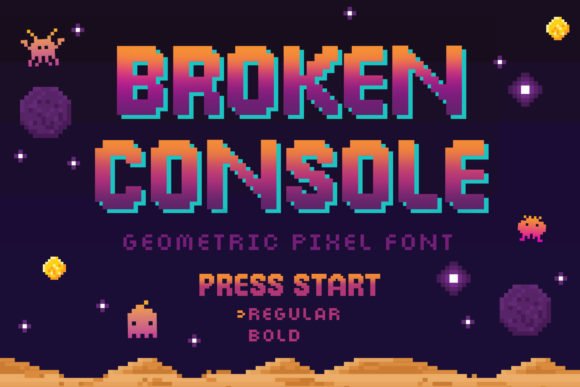
[Creativefabrica] Broken Console Font (2021)
Broken Console - это современный и футуристический шрифт.
Этот шрифт идеально подходит для написания веб-дизайнов, визитных карточек и практически всего, что требует холодного штриха.